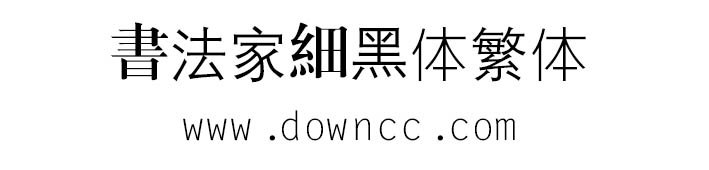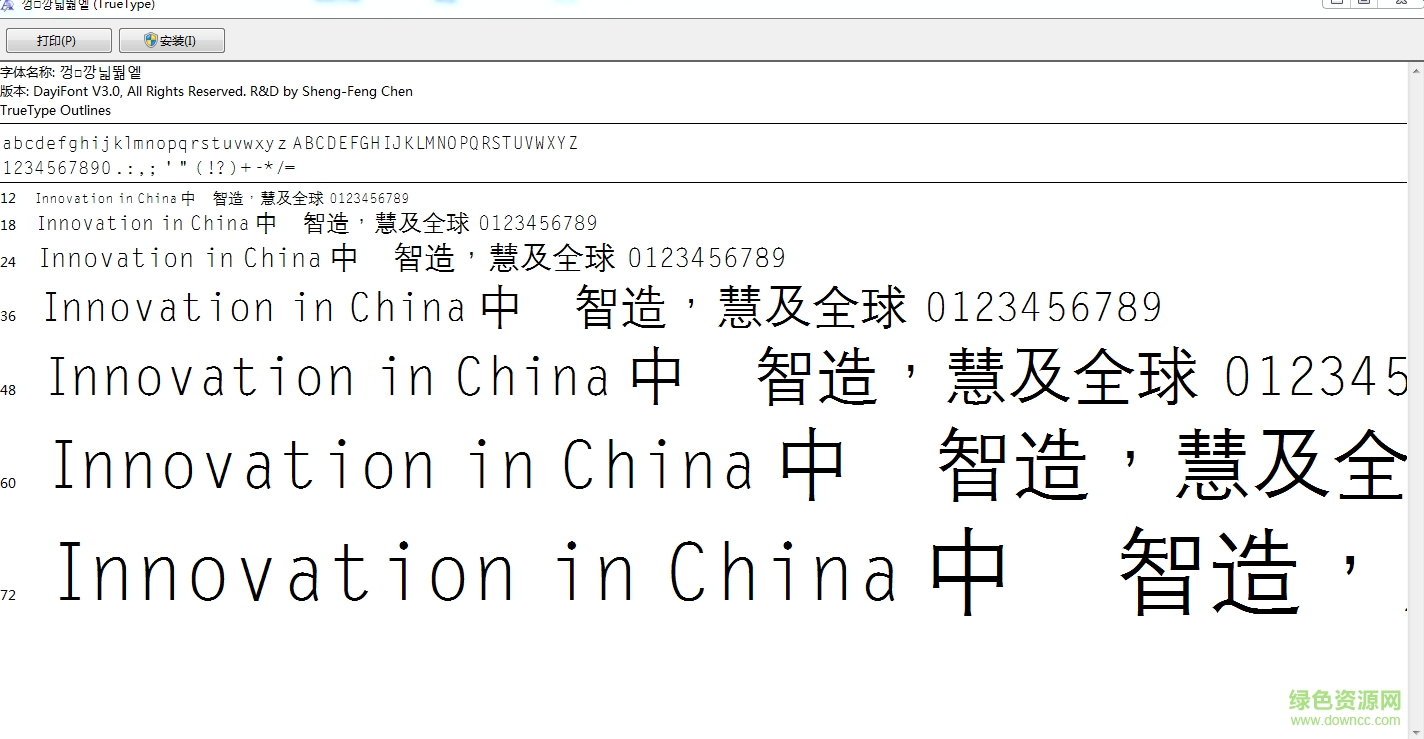
書法家細(xì)黑體繁體是一款細(xì)條細(xì)膩的繁體中文漢字,該字體以黑體為原形,字形端正大方,并且字庫完整,整體效果非常出眾,能夠適用于包裝印刷、廣告設(shè)計、平面設(shè)計、書籍報紙等領(lǐng)域,喜歡的朋友快來綠色資源網(wǎng)下載收藏吧。
書法家細(xì)黑體繁體給人的感覺是很端正,它的一橫一豎都特別的直,并且筆畫又細(xì),好似一種裝飾的字體的字體而不是書法。